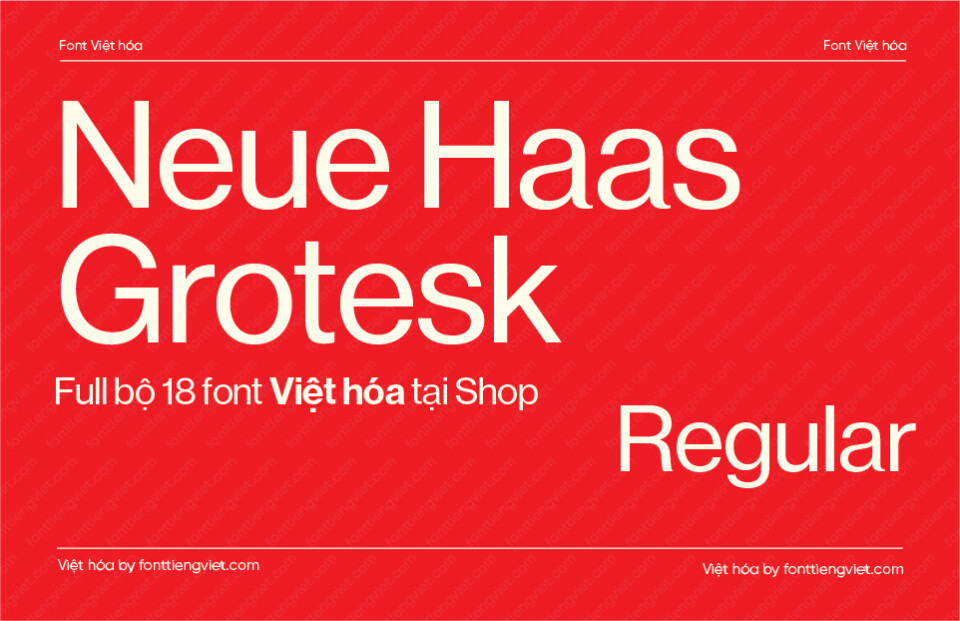
Tải Font Việt hóa 1FTV VIP Neue Haas Grotesk Regular miễn phí cho thiết kế chuyên nghiệpGiới thiệu về Font Việt hóa 1FTV VIP Neue Haas Grotesk RegularTrong thế giới đồ họa hiện đại, việc lựa chọn một bộ Font Miễn Phí chất lượng đóng vai trò quyết định đến sự thành công của một bản thiết kế. Font Việt hóa 1FTV VIP Neue Haas Grotesk Regular là một phiên bản đặc biệt, được tinh chỉnh kỹ lưỡng để phù hợp với ngôn ngữ tiếng Việt. Đây vốn là tiền thân của phông chữ Helvetica lừng danh, mang trong mình vẻ đẹp nguyên bản của trường phái thiết kế Thụy Sĩ. Sự xuất hiện của biến thể 1FTV VIP giúp các nhà thiết kế Việt Nam tiếp cận gần hơn với những tiêu chuẩn thẩm mỹ quốc tế, đồng thời đảm bảo tính ứng dụng cao trong các tài liệu học tập và giảng dạy tại trường học.Đặc điểm nổi bật của Font Việt hóa 1FTV VIP Neue Haas Grotesk RegularSự tinh tế trong từng đường nét thiết kếĐặc trưng lớn nhất của Font Việt hóa 1FTV VIP Neue Haas Grotesk Regular chính là cấu trúc hình học cân bằng và độ tương phản thấp. Khác với các phông chữ hiện đại thường cố gắng tạo ra sự phá cách, Neue Haas Grotesk giữ lại sự chân thực và rõ ràng. Các dấu tiếng Việt được đội ngũ 1FTV xử lý khéo léo, không làm phá vỡ cấu trúc gốc của chữ cái, giúp văn bản trở nên thanh thoát và dễ đọc hơn bao giờ hết. Điều này cực kỳ quan trọng đối với các bạn học sinh khi trình bày bài tập lớn hoặc các thầy cô soạn thảo giáo án điện tử.Tính đa dụng trong môi trường học đường và chuyên nghiệpKhông chỉ dừng lại ở các ấn phẩm quảng cáo, Font Việt hóa 1FTV VIP Neue Haas Grotesk Regular còn thể hiện ưu thế vượt trội trong việc dàn trang sách và làm slide thuyết trình. Với độ dày vừa phải (Regular), phông chữ này giúp mắt người xem không bị mỏi khi theo dõi các nội dung dài. Sự trung tính của nó cho phép kết hợp linh hoạt với nhiều phong cách khác nhau, từ cổ điển đến hiện đại, giúp thông điệp truyền tải một cách khách quan và uy tín nhất.Cách ứng dụng Font Việt hóa 1FTV VIP Neue Haas Grotesk Regular hiệu quảSử dụng trong thiết kế giao diện và in ấnKhi sử dụng Font Việt hóa 1FTV VIP Neue Haas Grotesk Regular, bạn nên chú ý đến khoảng cách giữa các chữ cái (kerning). Việc giữ khoảng cách tiêu chuẩn sẽ phát huy tối đa vẻ đẹp tối giản của bộ font này. Trong in ấn, đây là lựa chọn hàng đầu cho các tiêu đề phụ hoặc nội dung thân bài (body text) vì độ sắc nét cao, ngay cả khi in ở kích thước nhỏ. Đối với các trang web giáo dục, bộ font này tạo cảm giác tin cậy và chuyên nghiệp cho người truy cập.Lưu ý khi phối hợp các bộ font chữĐể tạo nên sự hài hòa, bạn có thể kết hợp Neue Haas Grotesk với các font chữ có chân (Serif) để tạo sự tương phản mạnh mẽ. Tuy nhiên, bản thân Font Việt hóa 1FTV VIP Neue Haas Grotesk Regular đã đủ mạnh mẽ để đứng độc lập trong các thiết kế mang tính tối giản (Minimalism). Việc sử dụng đồng nhất một bộ font trong toàn bộ tài liệu sẽ giúp tăng tính nhận diện và sự chỉnh chu cho tác phẩm của bạn.Kết luận về bộ phông chữ Neue Haas GroteskViệc sở hữu Font Việt hóa 1FTV VIP Neue Haas Grotesk Regular trong bộ sưu tập cá nhân sẽ giúp bạn nâng tầm thẩm mỹ cho mọi dự án. Đây không chỉ là một công cụ hỗ trợ trình bày mà còn là nguồn cảm hứng để tạo ra những sản phẩm sáng tạo chất lượng cao. Nếu bạn đang tìm kiếm một giải pháp typography bền vững và đẳng cấp, hãy trải nghiệm ngay tại Font Miễn Phí, Font Việt Hóa, Font Việt hóa 1FTV VIP Neue Haas Grotesk Regular để bắt đầu hành trình sáng tạo của mình một cách chuyên nghiệp nhất.
Font Việt hóa 1FTV VIP Neue Haas Grotesk Regular